Tipografies, un sitio de tipografía en catala, realizado por Jordi Embodas, Fer Rodríguez, María Ramos, Joancarles Casasín.
Este es magnífico sitio sobre tipografía, el Tipografies (tipografías en catalán), en su reseña dice algo así » Tipograpies está especializada en tipografías de texto consideradas más completas, útiles y duraderas.»
Tipografies, es un estudio de diseño tipográfico, que está reflejado en un bello sitio web. Es fundado en 2010 por diseñadores gráficos especialistas, es decir tipógrafos. Ellos son Jordi Embodas, Fer Rodríguez, María Ramos, Joancarles Casasín. De las manos de estos diseñadores la tipografía se vuelve un objeto preciado de diseño cotidiano, usable y legible en todo sentido, como tipografía y como objeto.
Este sitio es un excelente ejemplo de cómo se van migrando las comunidades a distintos lugares según la moda, el uso, la publicidad, la captación de clientes, ahora la comarcalización posa por la web, en mirar varios ejemplos, ve el rendimiento de los tipos en acción. Pero por suerte, la esencia de las mismas sigue siendo la misma, en este caso «El producto final» la tipografía con rasgos modernos, activos, sigue teniendo un trabajo excelente por parte de ellos.
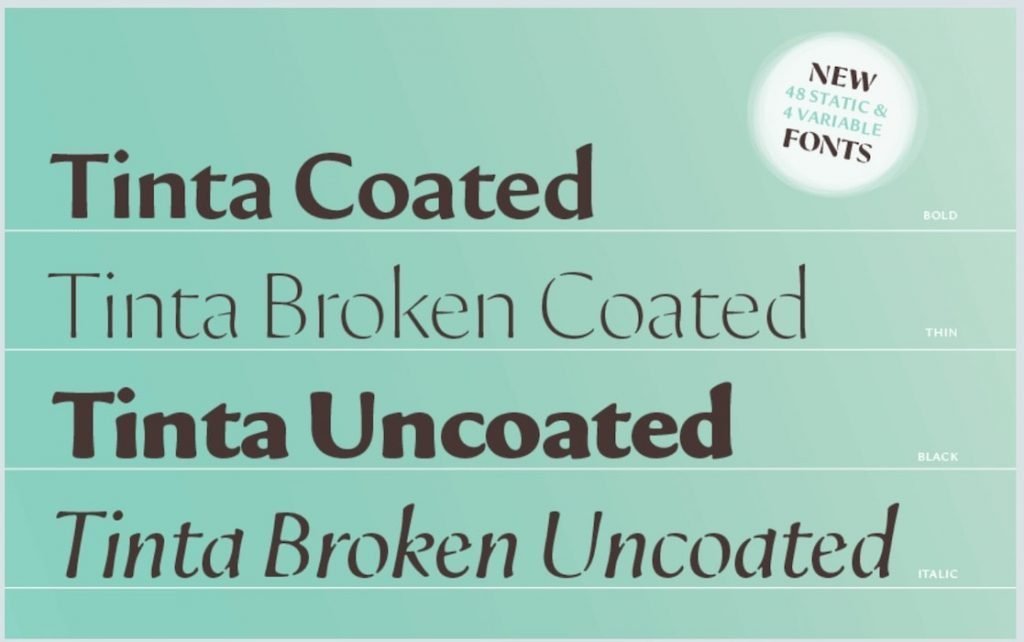
Todo este nuevo concepto es posible gracias a los vínculos que se dan entre la tecnología y que esta comunidad, en este caso tipografica, que supo aprovechar la movida.
El trabajo tipográfico que se encuentra al entrar a Tipografies es excelente, lleno de dinamismo, color, morfología, un estupendo tratamiento de nuestras queridas tipografías antiguas y modernas, siendo ellas las vedettes de la escena.
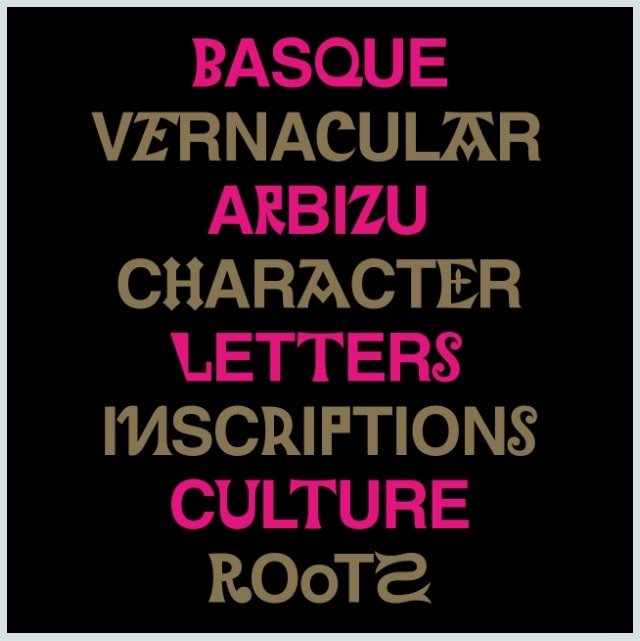
Ellos llevan a cabo entre otras cosas la transformación de tipografías antiguas en modernas para un uso cotidiano exacto, además de crear sus propias familias.
Tipografía ayer, hoy y siempre, realizada por excelentes diseñadores como estos, me remiten a aquellos como Stanley Morrison, Fermin Didot, Claude Garamond